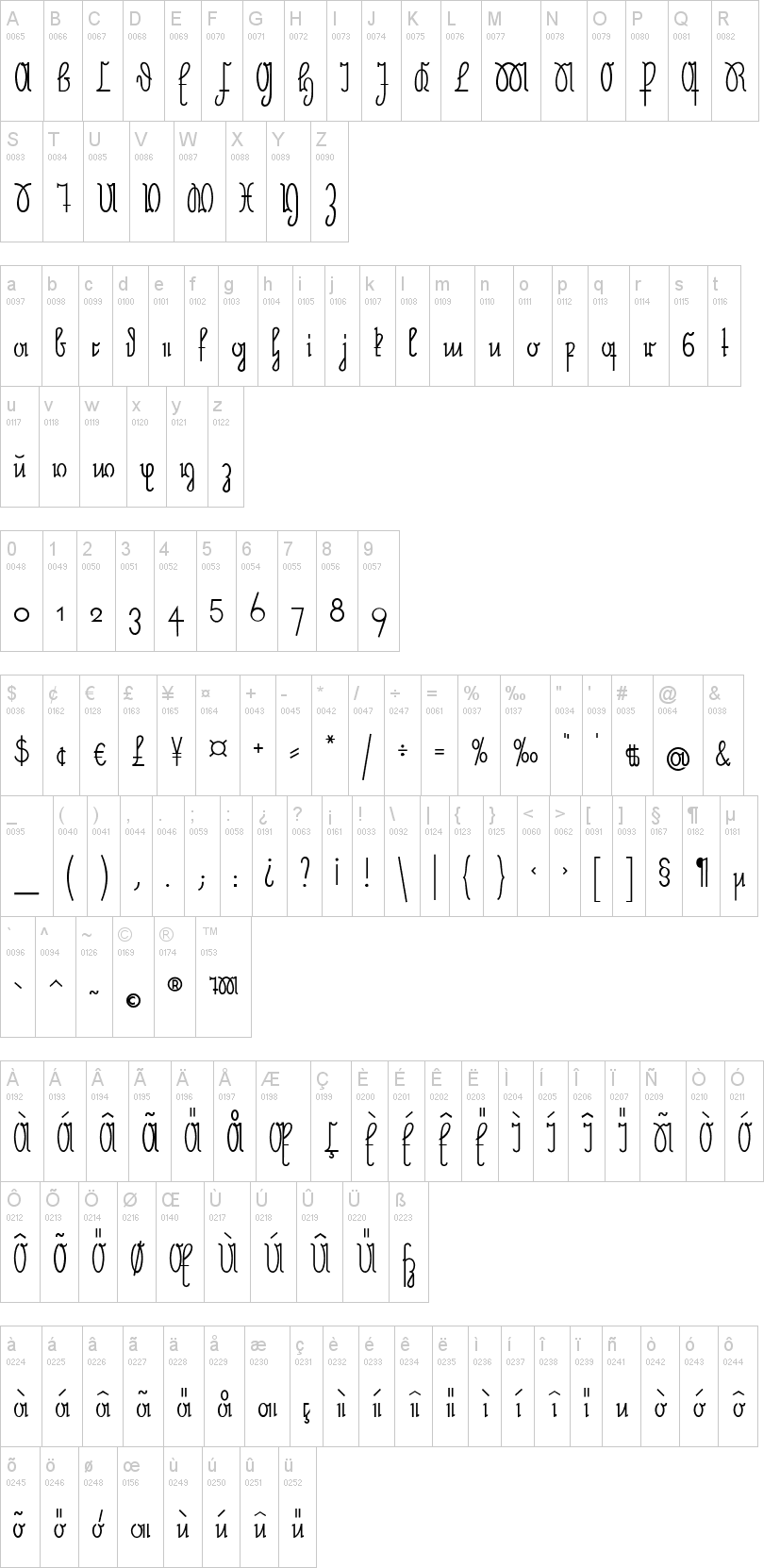
Neue Rudelskopf-Schraeg.ttfNeue Rudelskopf Stark.ttfNeue Rudelskopf Stark Schraeg.ttfNeue Rudelskopf Verbunden.ttfNeue Rudelskopf Verbunden Schraeg.ttfNeue Rudelskopf Verbunden Fett.ttfNeue Rudelskopf Verbunden Schraeg Fett.ttfNote of the authorDie "Neue Rudelskopf" ist ein neuer Ansatz, eine Schriftart zum Erlernen alter Handschriften anzubieten. Die Schrift gibt es - und das ist neu - in einer unverbundenen, quasi Blockschrift-Form, die aber auf den Buchstabenformen der spitzen "deutschen" Schreibschrift basiert, und damit die Erkennung der Buchstaben erleichtert, daran schließt sich mit den gleichen Buchstabenformen eine verbundene Schriftart an, die aber einen deutlich größeren Abstand (also längere Verbindungsstriche) als die Buchstabenbreite selbst besitzt, um für ungeübte fast nur als Sägezähne aussehende Wortbilder zu vermeiden.
Die Schrift hat volle UNZ1-(Unicode)Schreibschrift-Belegung